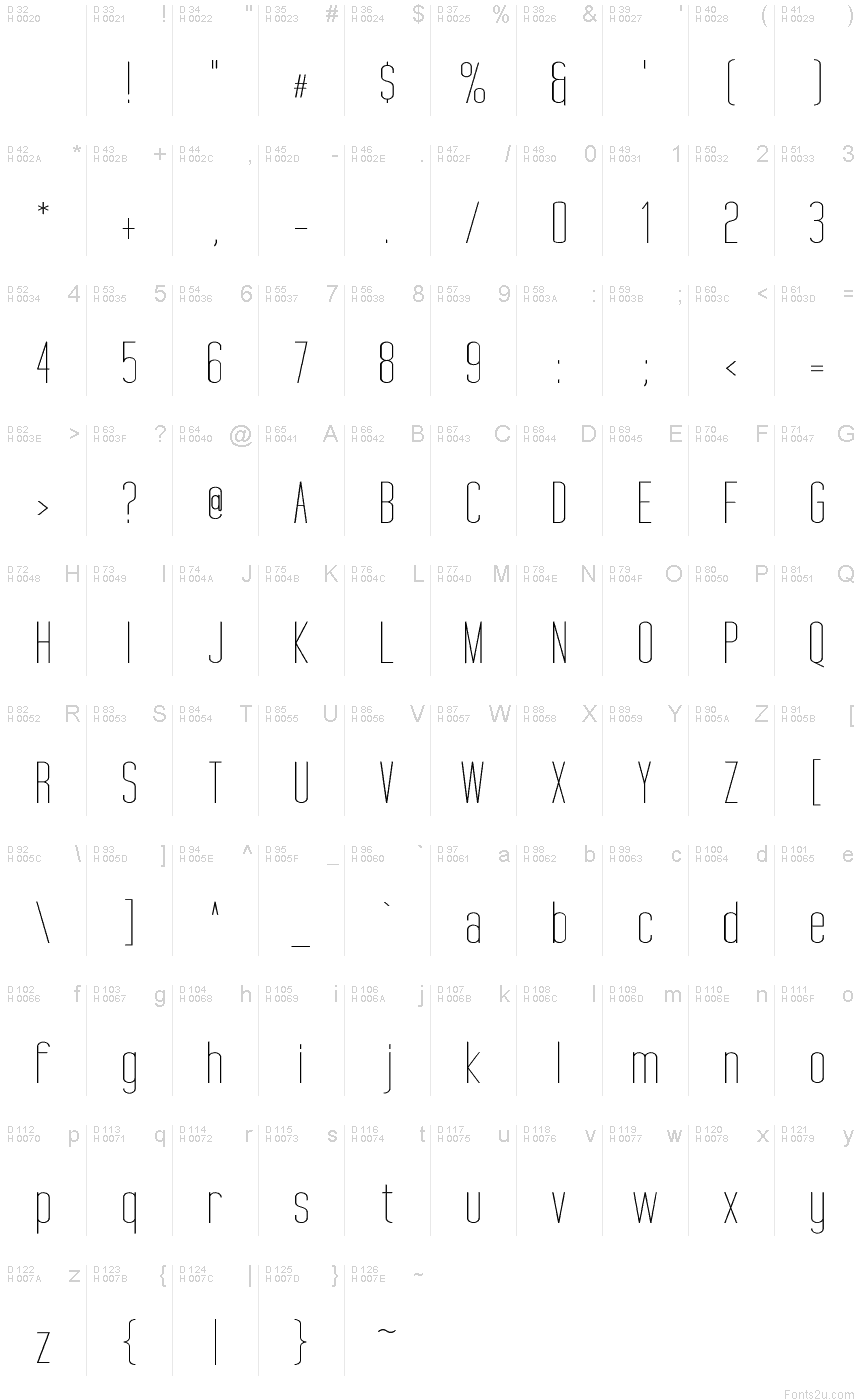
Tall Films Expanded to darmowy, wysoki krój bezszeryfowy od Grahama Meade’a. To minimalistyczny font displayowy o kinowym klimacie, wprost stworzony na plakaty. Litery wznoszą się w długich, równych pociągnięciach, a zaokrąglone małe litery przełamują ich wysokość, dzięki czemu całość nie sprawia wrażenia zimnej czy sztywnej.
Naturalnie pasuje do plakatów filmowych, plansz tytułowych, okładek płyt, nagłówków w magazynach i brandingu modowego, gdzie liczy się pionowy rytm. Jako darmowy font świetnie sprawdzi się też w krótkich nagłówkach internetowych i inicjałach typu monogram, szczególnie gdy zależy Ci na smukłej sylwetce i dużej ilości światła między mocnymi, pionowymi znakami.